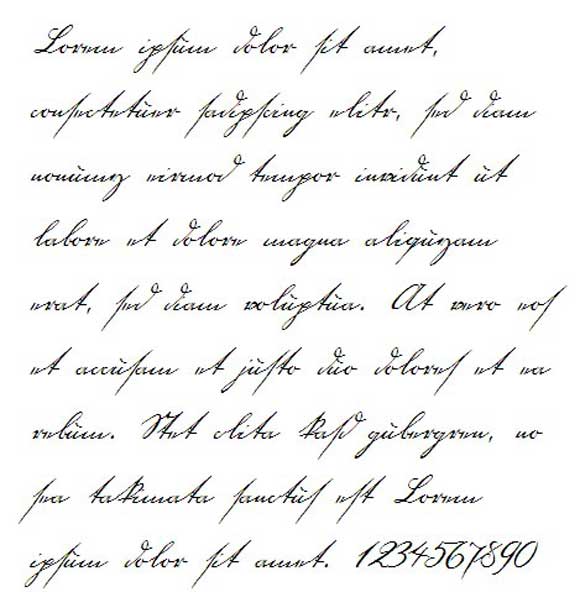
Шрифт как от руки в ворде: Как сделать шрифт от руки в word?
Как сделать шрифт от руки в word?
Хорошая новость для студентов, которым нужен рукописный конспект лекций для сдачи зачета или экзамена.
Пользователь сайта Pikabu под ником MakeMeHateYou опубликовал инструкцию по созданию поддельного рукописного конспекта в Microsoft Word.
Шаг 1
Создать страницу с размерами 165 на 205 мм, а также задать поля: верхнее и нижнее — 5 мм, левое — 25 мм, правое — 8 мм.
Шаг 2
Создать любую фигуру из вкладки «Вставка».
Фигура нужна только для того, чтобы в Word включилась вкладка «Средства рисования», где в разделе «Выровнять» можно найти пункт «Параметры сетки».
Шаг 3
С помощью «Параметров сетки» нужно создать клеточную разметку («Показать сетку») с шагом в 5 мм — как у обычной тетради.
Шаг 4
Скопировав текст из методички или «Википедии», нужно подогнать таким образом, чтобы он был написан по всем правилам — через строчку и с автоматическими переносами.
Главная находка MakeMeHateYou — шрифт Escal, который действительно очень похож на рукописный текст.
Шаг 5
После печати, склеивания между собой половинок листов скотчем, а также соединения их с помощью скоб с обложкой обычной тетради, у MakeMeHateYou получился правдоподобный на вид конспект.
По словам автора, молодых преподавателей таким образом вряд ли удастся провести, а вот с теми, кто постарше, он может сработать.
Хочу рассказать вам и показать на конкретном примере как сделать рукописный текст на компьютере при помощи текстового редактора Microsoft Word.
Также вы узнаете, как данный текст на принтере в формате тетрадного листа в клеточку.
Создадим тетрадный лист в клетку
1. Откроем Word, во вкладке Вид выберем ориентацию страницы Разметка страницы.
2. Открываем вкладку Макет, выбираем инструмент Размер.
3. В открывшемся окне выберите пункт Другие размеры бумаги…
4. В меню Параметры бумаги пункт Размер бумаги создадим тетрадный лист с реальными размерами. Размеры тетрадного листа 16,5×20,5 см, но при распечатывании на принтере получается меньше чем нужно во всяком случае у меня так, поэтому немного увеличить до 19,5×22,5см.
5. Пункт Поля поможет выставить параметры полей, где Верхнее и Нижнее должно быть по 0,5 см. Левое 2,5, а Правое 0,8 см. Подтверждаем намеренность своих действий кнопкой ОК.
6. Теперь осталось включить Сетку настроив ее размеры, для этого во вкладке Макет заходим в инструмент Выровнять — ставим галочку Отображать сетку. после сразу откроем Параметры сетки.
7. В параметрах нужно просто выставить размер клеток, который равняется как известно 0,5см.
Long CangШрифт Long Cang основан на почерке каллиграфа. Он имеет буквы разного размера, что вместе делает его более неровным и реальным.
Finger Paint — результат эксперимента с различными эффектами кисти. Шрифт явно показывает мазки под разными углами, которые завершают общий вид.
Сью Эллен ФранцискоЭтот шрифт основан на собственном почерке типографа Кимберли Гесвейн. Шрифт показывает высокие тонкие кривые линии, демонстрирующие особенности ее собственного почерка.
Самодельное яблоко — рукописный шрифт с эффектом меловой пыли.